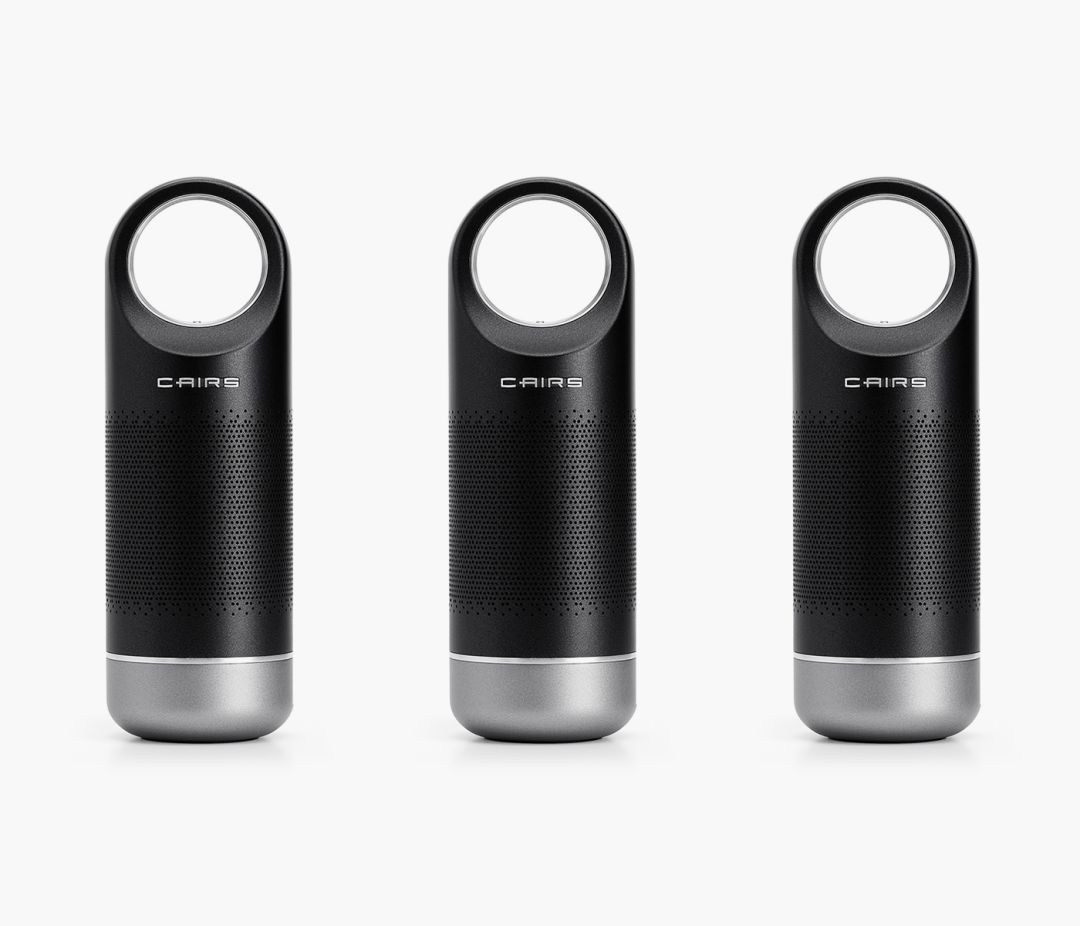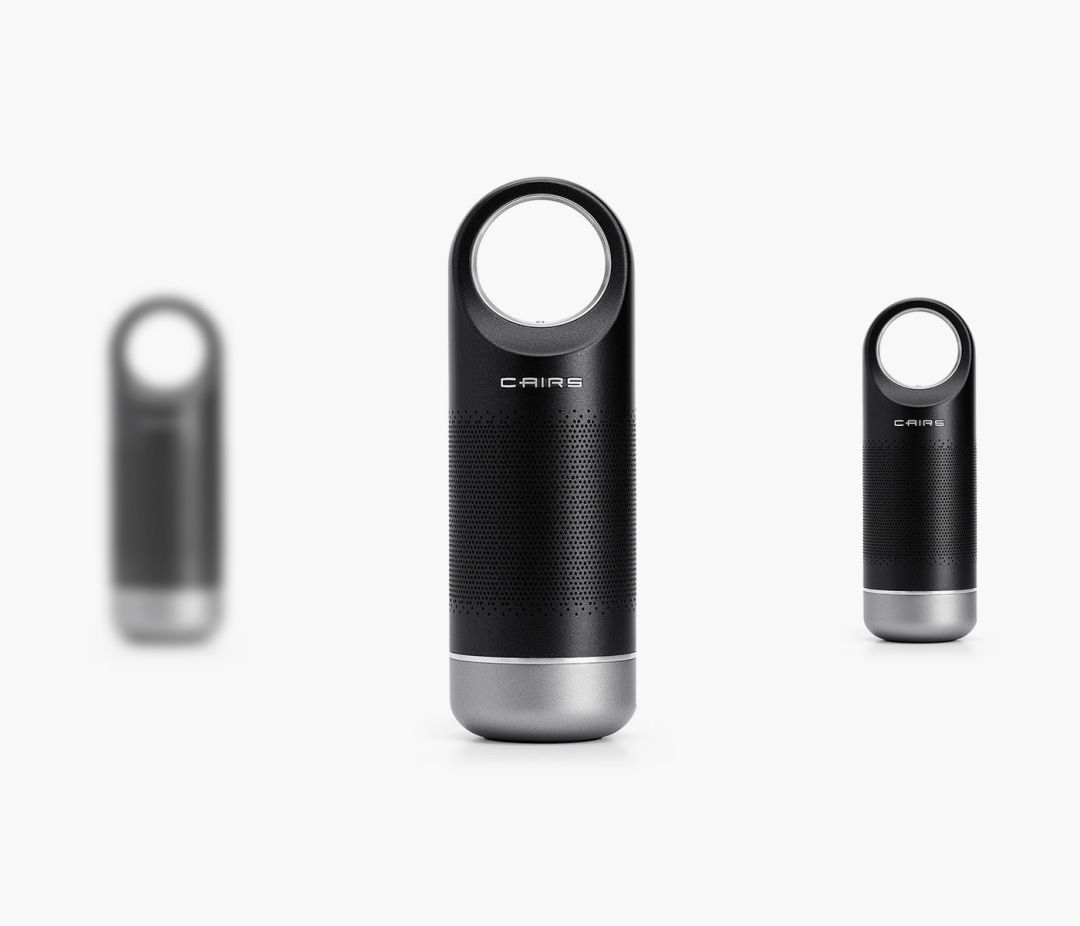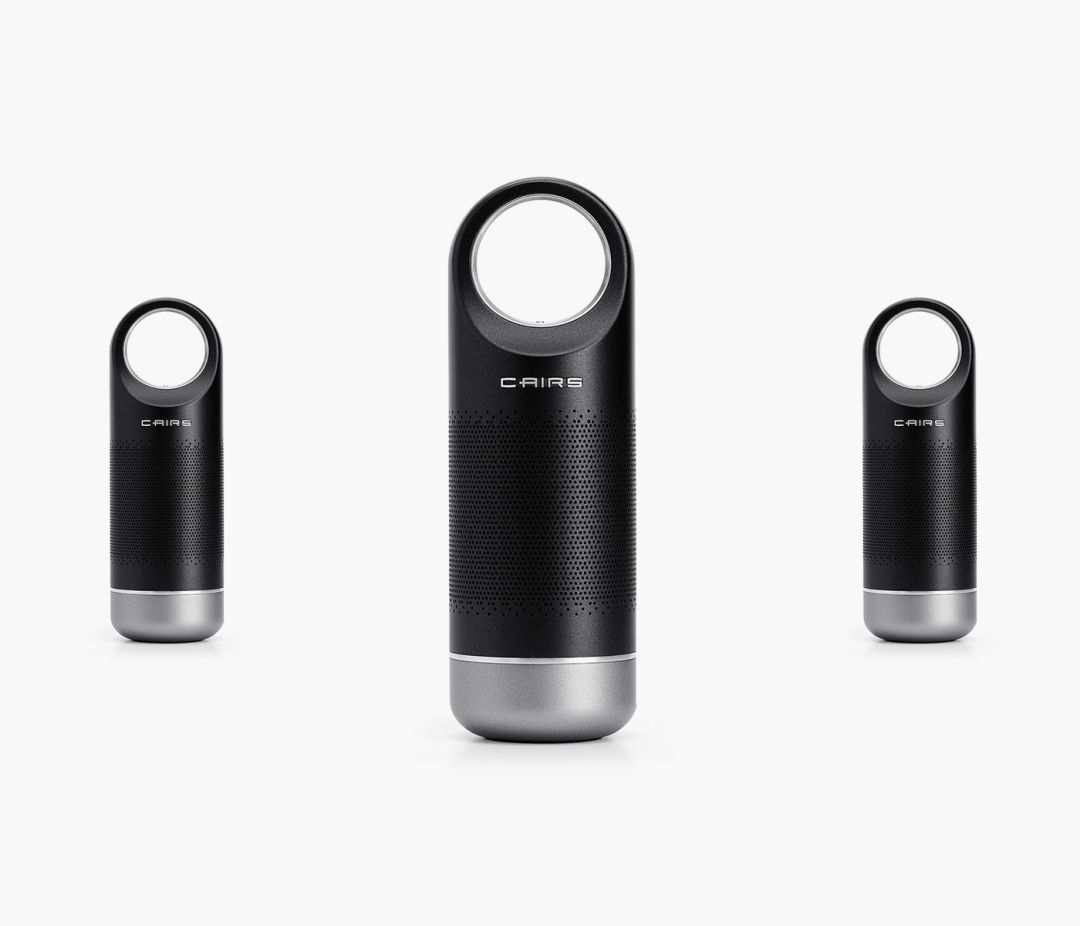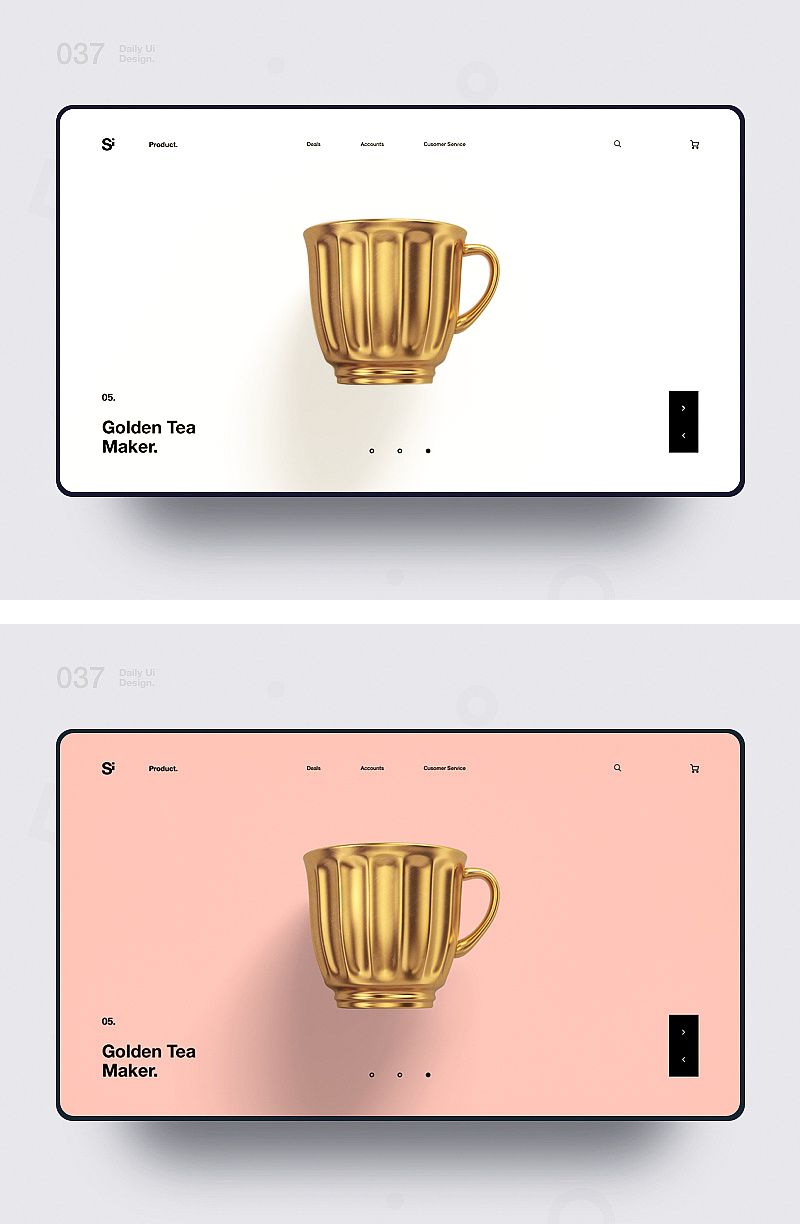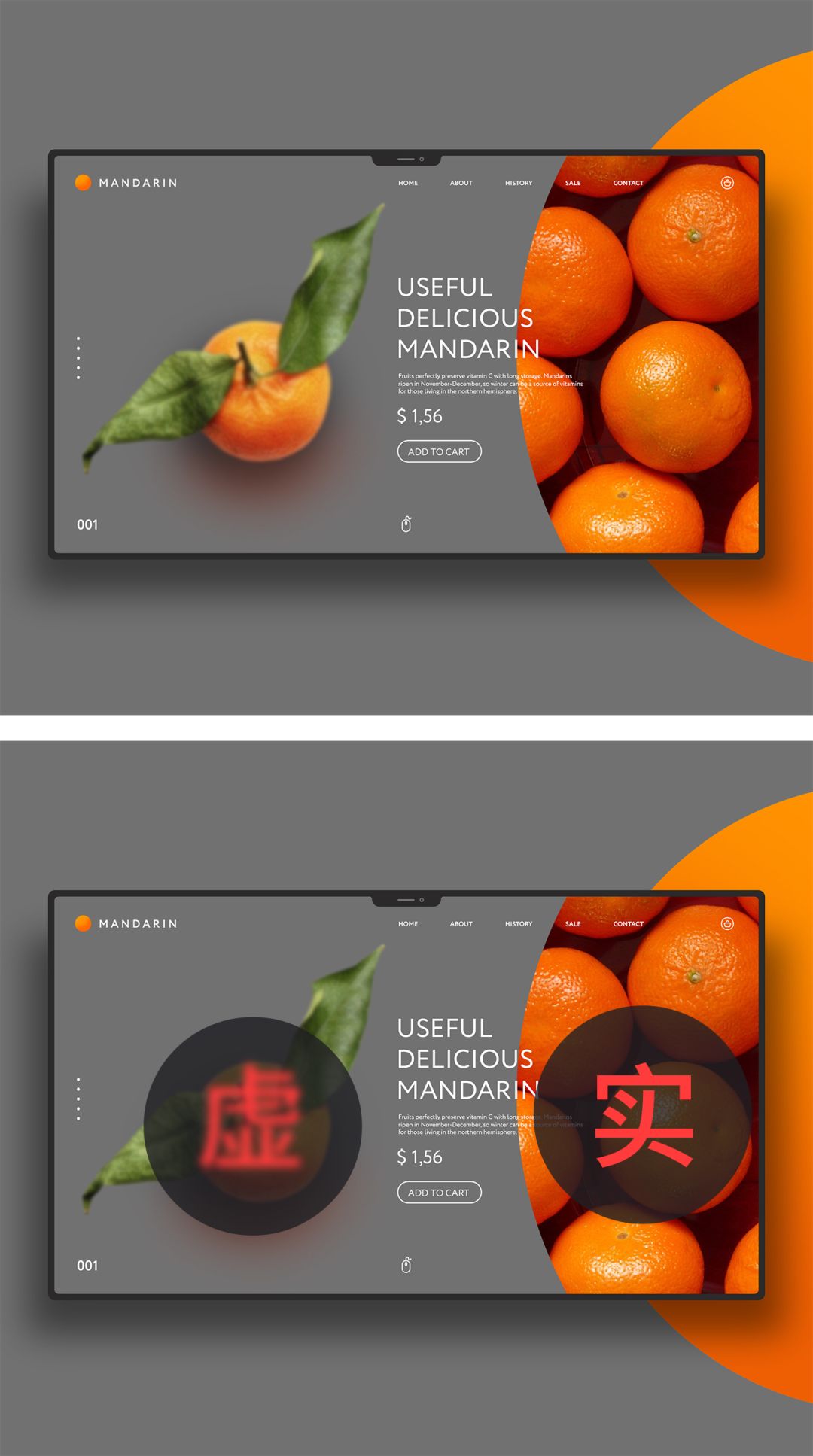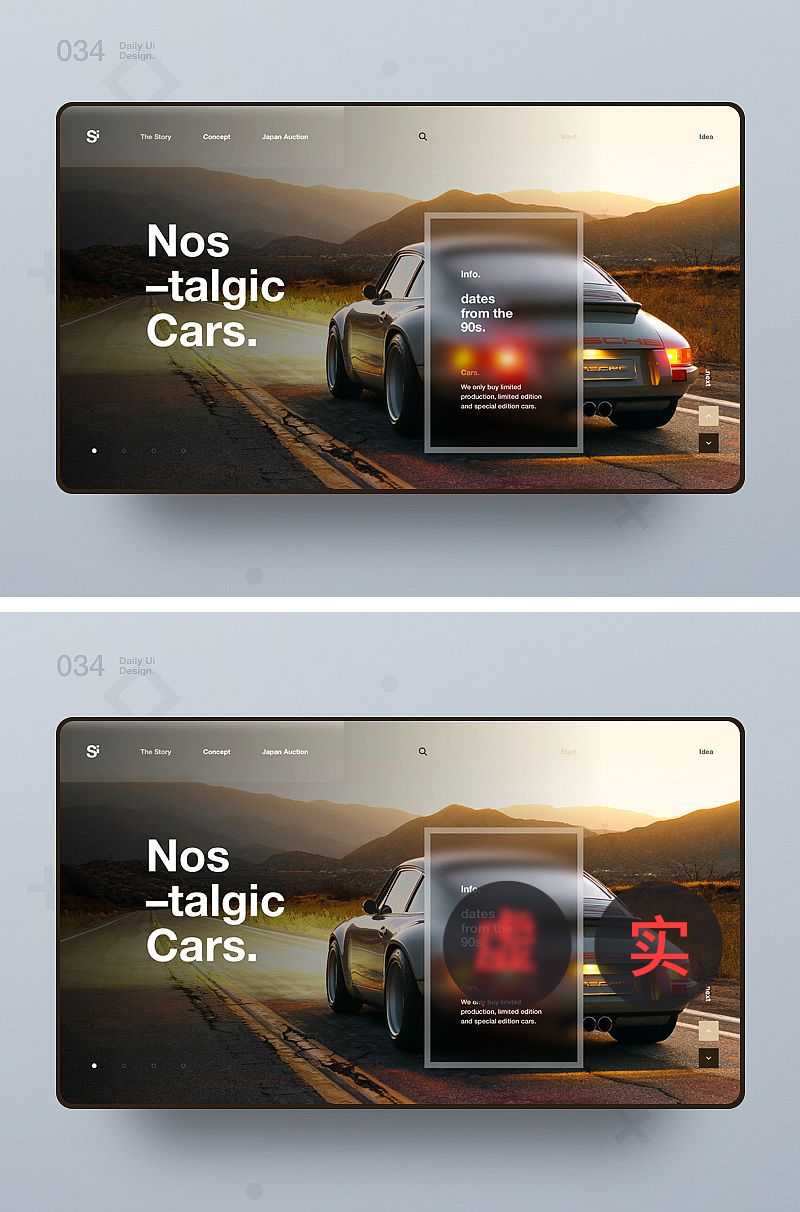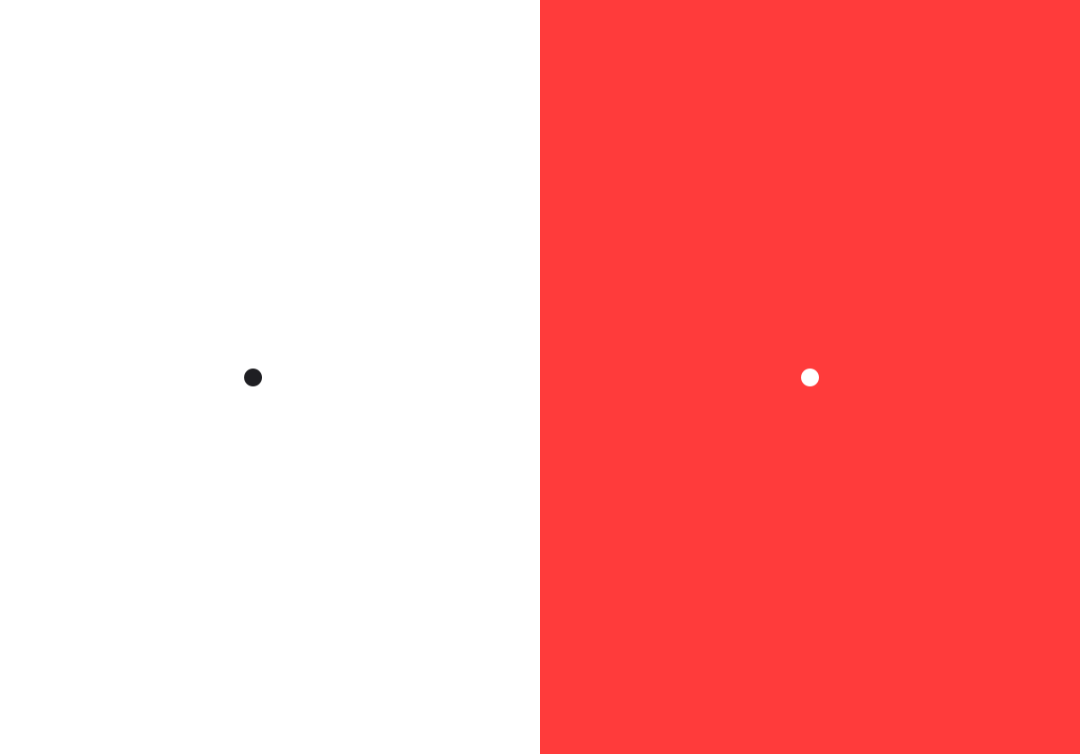
设计作品视觉缺少层次感,应该怎么解决?
“层次感”这个词在设计中的出现频率是很高的,主要体现在信息层级关系和视觉丰富度这两点,而缺少层次感的设计会给人一种信息杂乱、画面单调的视觉感受,甚至枯燥、乏味,这也恰恰与设计目的相悖!那么当我们的作品的出现层次感缺失时,应该从哪些方面着手改善、解决呢?本期内容希望能对大家有所帮助。
营造视觉元素的差异化可以起到很好的改变画面信息层级关系的作用,从而增强设计作品的层次感,这和对比手法很雷同,无论是画面中的视觉元素多还是少,都要做到有主有次、有大有小、有粗有细、元素与元素之间形成对比关系,举个简单的例子:
很明显第一排的形状之间是完全相同的,在视觉上给人的感觉就会很平,缺少变化;而下面两排在视觉上都营造了一个与周围存在存在差异化的视觉元素,使得整体在视觉上有了阅读的先后顺序,形成了简单的信息层级关系!
当画面中的视觉元素相同或者相似时,信息的层级关系就相对而言不容易体现出来,那么此时就需要我们营造具有差异化的视觉元素打破这一现象,从而增强画面的视觉层次感,无论切入点是什么。再比如我们看到的风景照:
从近到远在视觉上存在着很明显的差异化,比如:近实远虚、近大远小、近处的饱和度高远处饱和度低、近处的明度暗远处的明度亮等等,大自然的风景本身就能很好的诠释视觉层次感,所谓“设计源于生活”正是如此。那么这些应用到设计中应该如何体现呢?下面再看一个例子:
如果产品这么摆放的话,那么何来层次感而言呢?只能理解为重要的事情重复三遍。做个小小的改变:
画面有了大小关系,故而有了主次关系,此时视觉的层次感已经有所体现:
大小与虚实的双重结合,视觉层次感更加强烈了,加点透视看看:
这里做了点透视效果,结合大小、虚实的变化,是不是有种由近到远的既视感,通过营造视觉元素的差异化,视觉层次感也更加强烈,这种虚实结合的形式在设计中也非常实用,下面我们再看案例:
这种虚实对比的形式也是视觉元素差异化体现形式之一,很直观的提升了整体的视觉层次感,包括在一些文字排版也很实用。所以当我们的作品整体视觉层次感不够强烈时,不妨试试通过营造视觉元素差异化的形式进行提升和改变,只是既然用了这种表现手法,就要做的足够明显,否则只会适得其反。
我们前面说了,提升视觉层次感可以从两个点切入,即:提升信息层次感以及画面整体丰富度,而装饰性元素的使用刚好可以契合这两点,它既有提升信息层次感的作用,又能起到很好丰富画面的作用,下面我们看个案例:
通过上下两个案例的对比我们发现:
第一:上侧案例画面整体的丰富度欠缺,甚至感觉有些空;而且文字信息没有形成很好的对比关系,信息的层次感受也比较单一,所以给人的感觉层次感不够。
第二:下侧案例中用到了一些装饰性的文字、线条、形状符号等,首先在视觉丰富度上较上侧案例中就提升了很多,不会给用户一种空的感觉;其次这些装饰性的元素与主文案在视觉上也形成了很好的对比,使得画面有了主次、大小之分,视觉形态的变化形式更多,视觉层次感也更加强烈。
第三:装饰性元素可以是文字、线条、形状、图形等等一些点状、线状的元素,甚至于一些块状元素(比如:水印文字、产品等),目的是通过增加画面丰富度和视觉形态变化的多样性提升整体视觉层次感。
需要注意:装饰性元素也不能过多的使用,因为过量的使用很容易在视觉上形成散乱、不够整体的情况出现,要根据实际情况合理使用!
使用肌理是设计中非常实用的一个设计手法,肌理有着很好的丰富画面、增加细节、提升层次感的作用,比如可以用作一些海报的底纹、文字的材质、甚至是一些形式感很强的肌理可以作为画面的抽象主体,下面举个例子:
案例中将远山风景图片通过透明度调整作为肌理使用,这样做的好处在于:首先肌理相较于整个画面来说不是那么显眼,这样就避免了抢了主体;其次因为远山给人的视觉感受就是层次感强烈,而这里当做肌理即起到了一定的填充、丰富的作用,又保留了一些远山的属性,在视觉上层次感更加强烈。
再比如一些文字也会使用肌理,用于增强文案信息的视觉层次感受,比如:
主要字体使用肌理会在让其形象更加鲜明,与正常文案形成很好的对比,也能间接的提升文字排版的视觉层次感。
当作品视觉层次感不够强烈时,我们可以转化为思考如何提升画面丰富度以及信息层次感,比如前面说的:对比、装饰元素、肌理都可以与之对应起来,那么为什么说合理的使用色彩在一定程度上也能起到提升视觉丰富度的作用呢?下面举个例子:
这里是通过有彩色与无彩色的案例对比,以视觉感受来看:左侧明显比右侧显得更空一些,因为色彩也是一种信息传达的媒介,也就是说颜色也在传递信息,所以当画面显得空、缺少层次感的时候,通过颜色的调整也能起到一定的增加视觉层次感的作用,举个例子:
这里只是改变了底色,在视觉丰富度上给人的感受差距一目了然,因为纯白底会给人一种空、缺少内容的视觉感受,所以一般情况下我们的处理方式会选择添加一些视觉元素,比如:装饰性元素、材质、线条等等,现在我们又多了一个选项,就是无彩色向有彩色的改变,虽然这种方法有一定的局限性,但是也不失为一种可行的解决方式。
其实这种营造前后叠加关系的方式在之前的文章中也提到过,其实就是寻找元素与元素之间的物理叠加关系,会给人一种很强烈的层次变化,对于提升画面层次感能起到立竿见影的作用,比如:
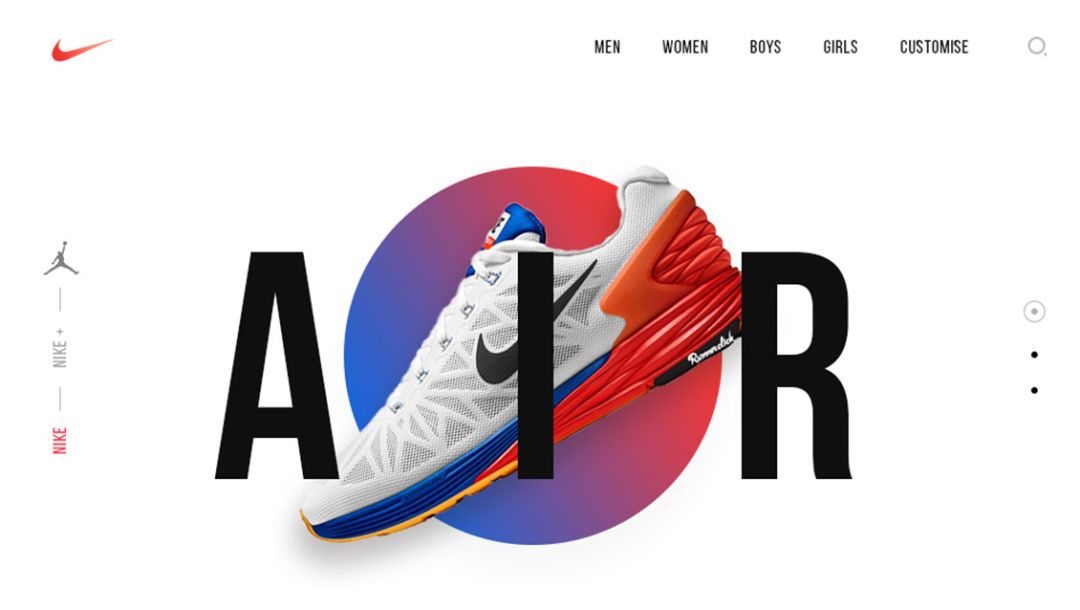
案例中的文字与主体物之间存在着视觉上的前后叠加关系,给用户更强烈的视觉层次感,这种营造前后叠加关系的处理手法在标题设计中也很实用。
透视也可以理解为营造空间关系的手法,当平面的视觉元素赋予其透视关系后,会形成一种类似三维空间的视觉感受,在一定程度上也能起到增强画面视觉层次感的作用,下面举个例子:
很明显,透视的感觉会给人一种空间感、延伸感,视觉层次更加强烈,这种形式在日常的设计中也很实用,比如:
改变透视会在视觉上形成一种纵向的延伸感,空间上层次关系更加强烈,只是这种形式有一定的局限性。
结合今天所说到的这些手法,通过不断演变的形式下面我们简单做一组文字排版的案例:
这就是一句普通的话,没有主次、没有修饰、毫无层次感,改变一下:
已经有了信息的层级关系,即大小对比,视觉元素之间形成了差异化的表现,还可以继续深入:
通过改变颜色,对比更加强烈,层次感稍加增强,感觉还不够?下面我们继续再改:
这里通过肌理、虚实结合以及改变字体形态的表现形式,使得整体视觉层次感又提升了一个档次,如果还想继续提升,那么就要想,还缺少点什么?比如装饰性元素试一试?
问:设计师,还能再强烈点吗?
答:emmm~我再试试(内心:头发都没了,MMP...)
增加了装饰性元素之后,画面整体的丰富度提升了很多,而且对比的形式更多元化;案例中主要用到了:差异化元素、对比、肌理、装饰性元素这四种表现形式,当然这不也许不是最好的表现形式,目的是为了让理论成为实践。
当作品缺少层次感时,上述的一些改变方法可以供大家参考,但是不要仅仅局限于这些,还有一些我们常用的,比如:投影就非常实用,可以给文字、色块、主体物等等做投影,拉开前后关系,这样也会一定程度上增强视觉层次感;再比如:倒影、环境感等等,这些目的都是尽可能的去丰富画面、营造信息层次关系。并不是说这些手法一定要完全体现在一个作品上,层次关系过多反而会使得画面整体乱,一定要根据实际情况选择使用,切记并不是视觉层次数越多就越好,这是一个误区。